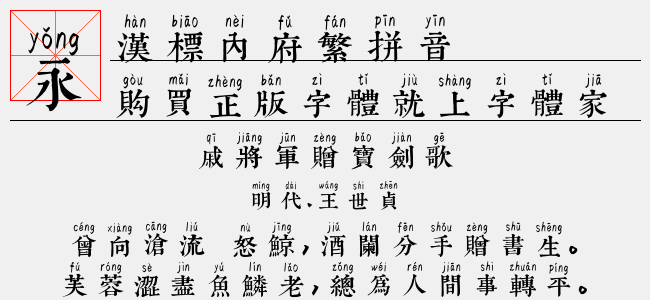
汉标内府繁拼音
字体作者:汉标字库
字体名称:汉标内府繁拼音
字体家族:汉标字库
书体类型:手写体
字体公司:汉标字库
汉标内府繁拼音是一款非常不错的艺术字体,书写行云流水,具有强烈的视觉冲击力,适应于报纸和杂志和书籍中常用字体, 海报、个性促进品牌标志设计、字体设计、等环境使用,欢迎喜欢的朋友前来字体家下载使用。